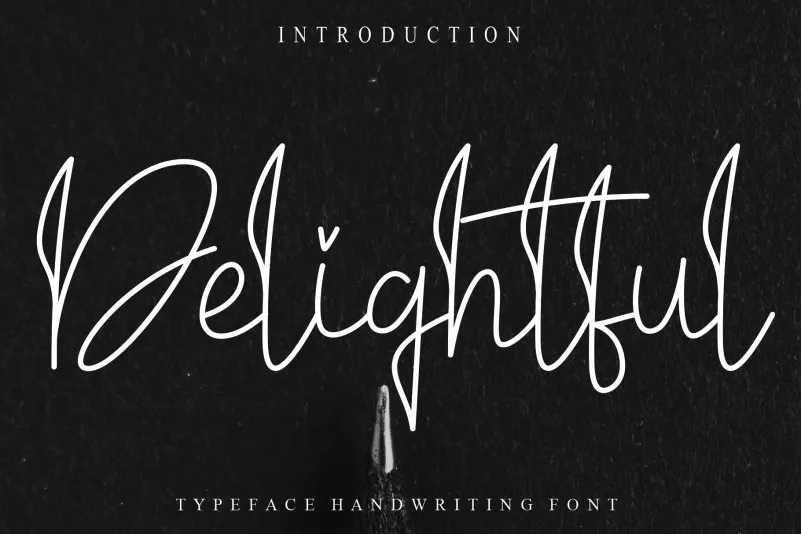
Na categoria de fonts para letra cursiva, a fonte Delightful Handwritten oferece uma experiência única e envolvente que vai transformar seu design de documentos digitais. Esta fonte foi criada pelo Designer CreativeLetter para fornecer um produto que irá surpreender você. Com linhas suaves e traços delicados, Delightful Handwritten é perfeito para aqueles projetos em que deseja criar uma impressão pessoal ou mais sofisticada. Ela combina facilmente com outros tipos de fontes para criar layouts elegantes e únicos. Seja em cartões de agradecimento, anúncios de marketing ou até mesmo no design de blogs e sites pessoais, Delightful Handwritten é a escolha perfeita que vai destacar seu trabalho. Através desta fonte criativa e personalizada, você consegue trazer uma sensação única para cada projeto.